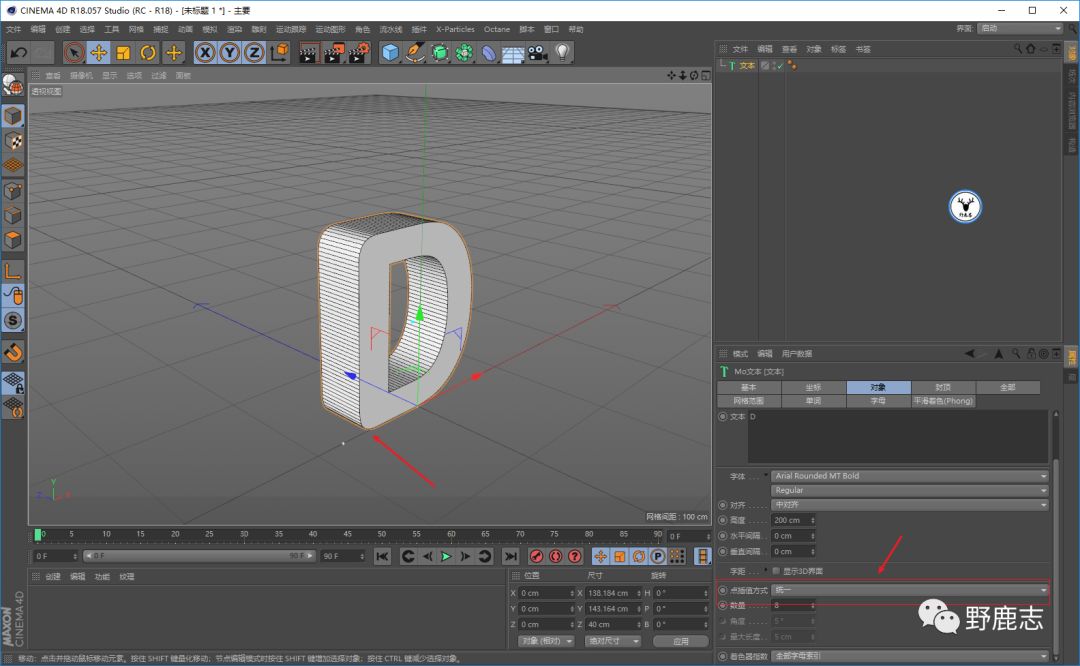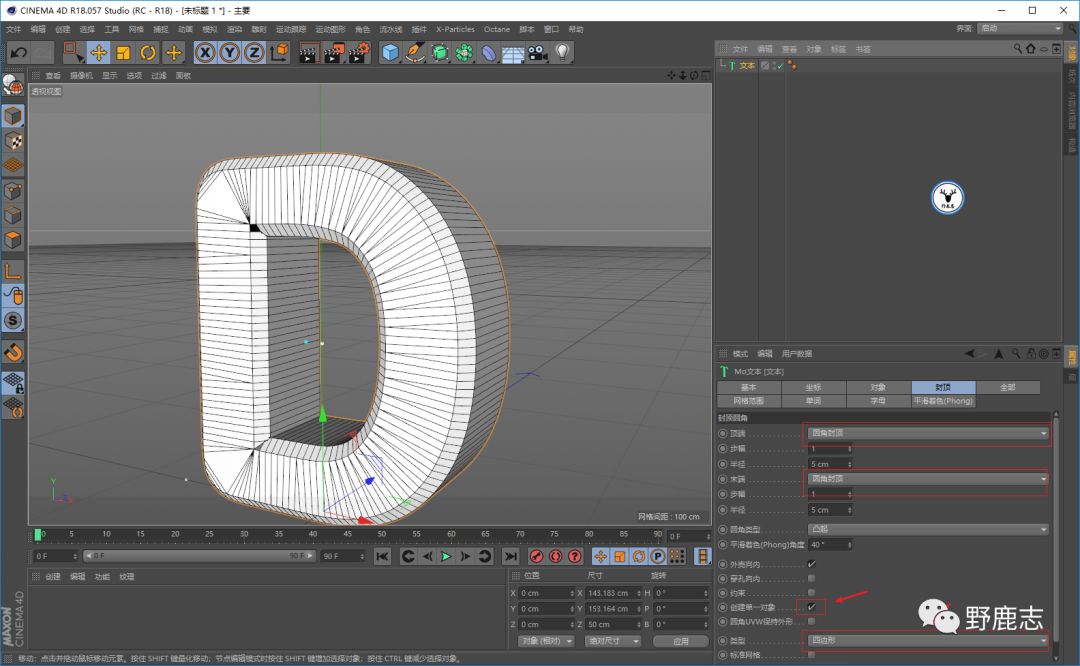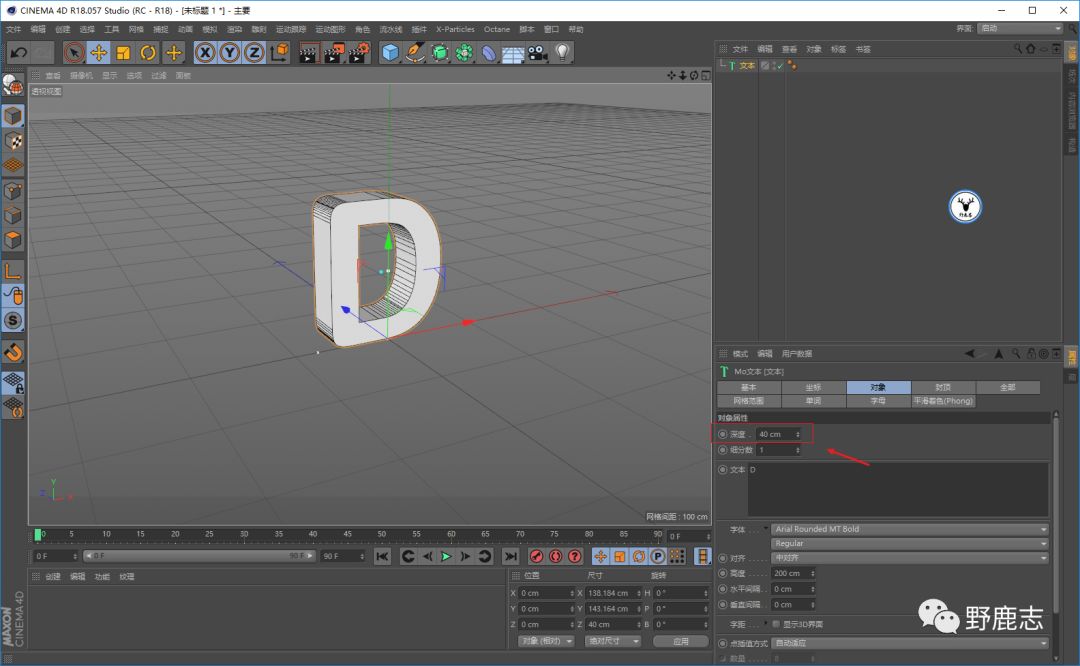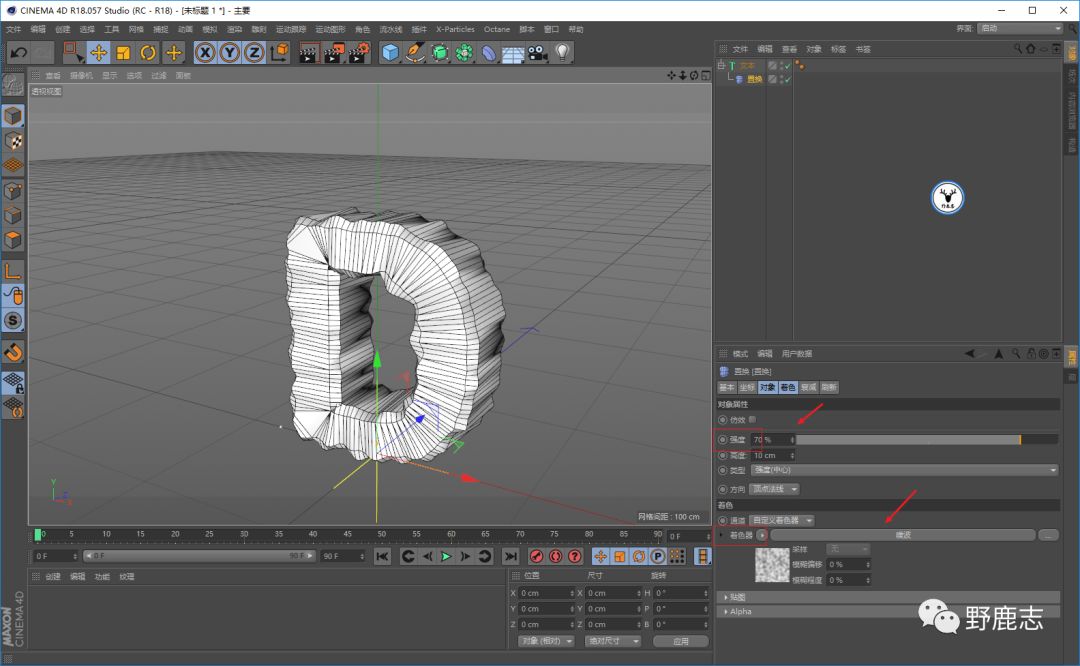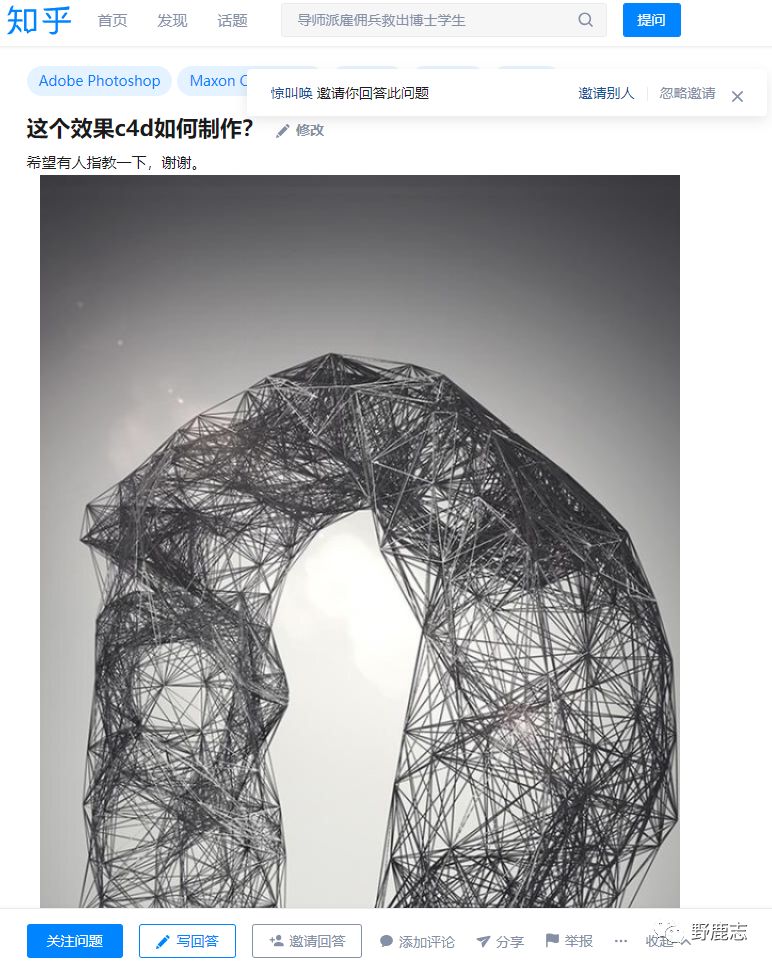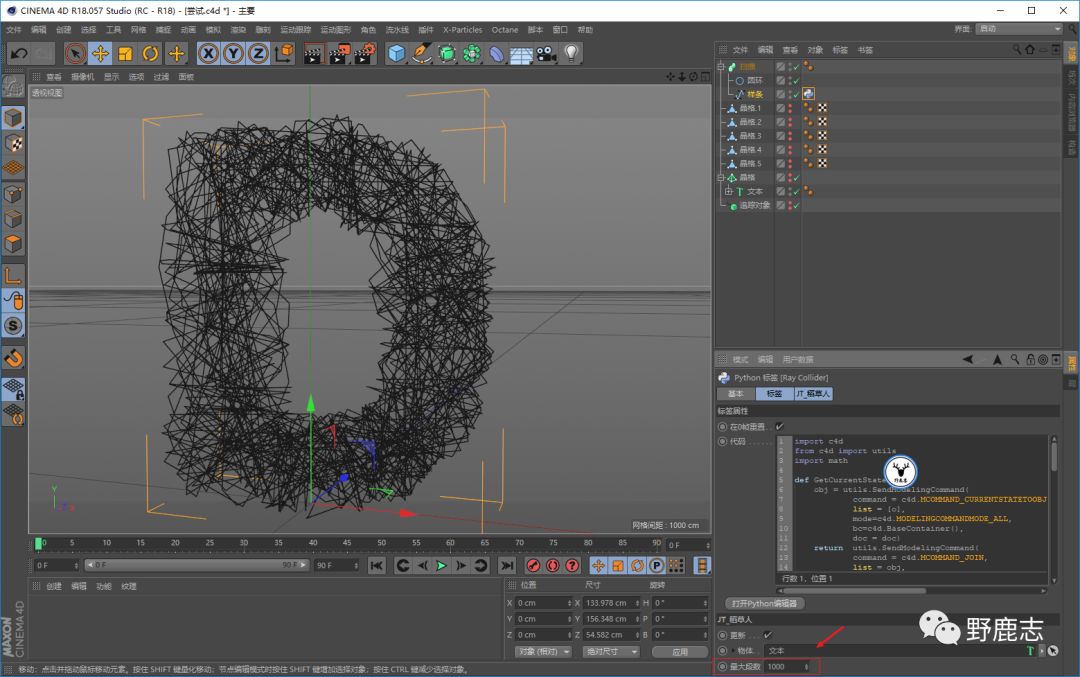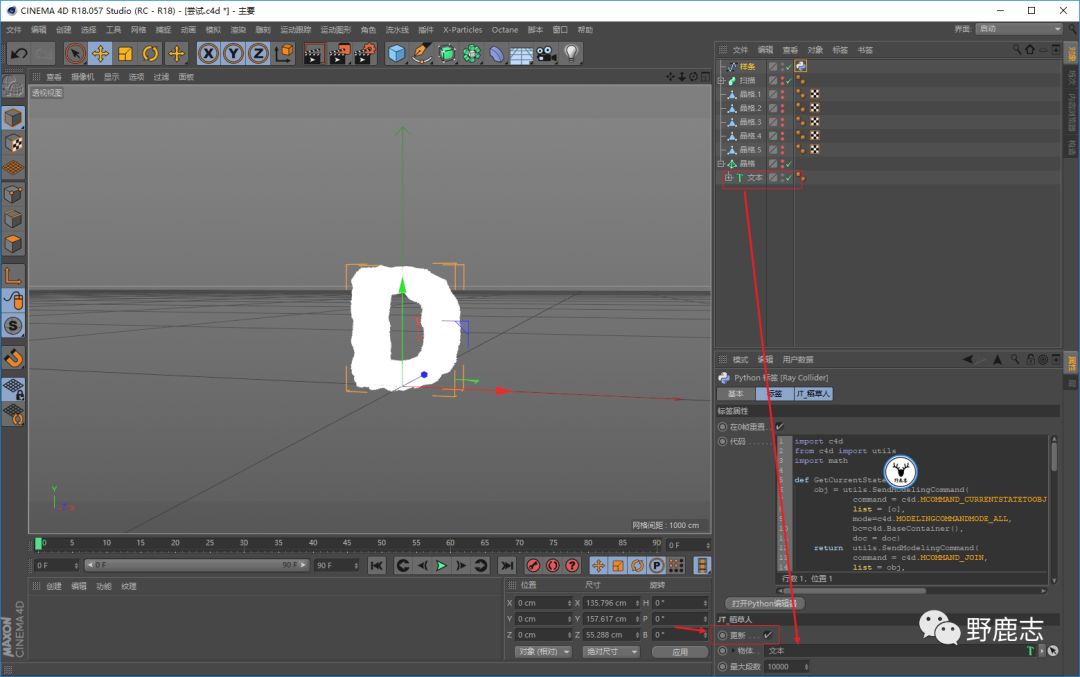
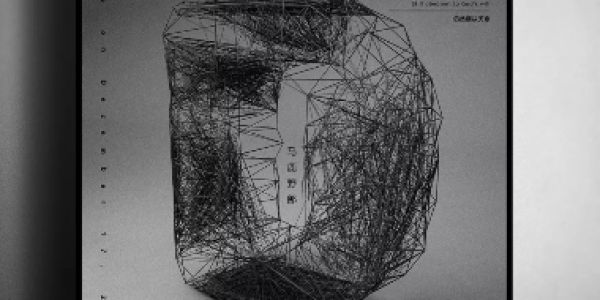
那种框架线条的效果是如何制作的?
我尝试了一下,大体方法其实不难,不过要做出好的效果还是需要花点功夫。
来吧,今天我们就用C4D来制作一个框架线条文字吧!
开始之前还是先大体分析一下原图,能够看出原模型字母的框架其实是有点low poly低多边形的感觉,所以我们要先做出一个低多边形的字母模型。
另外由于除了框架以外,框架内部还有许多不规则的线条,所以我觉得可能要做两层才可以。
第一层由于晶格是根据模型的布线来使模型产生变化,所以做好low poly的字母模型以后,我们尝试用晶格来做。
第二层的线条我打算用追踪对象来做,追踪对象不仅可以追踪路径,还可以把各个点连接起来。
大概初步分析就这么多,具体做的时候我们再看吧。
打开C4D,新建文本:
选择一个觉得合适的字体,适当的增加深度,由于我们后面要使用到晶格,所以把光影着色线条打开,方便观察:
点差值方式改为统一,让布线更加均匀一点:
封顶里面把圆角封顶选上,参数默认就可以了,勾选创建单一对象,类型选择为四边形:
添加一个置换变形器,着色面板添加一个噪波,然后适当的调整置换的强度,这一步不用多说吧:
再添加一个减面效果器,适当的调整强度,这样模型上的布线就都成了三角面:
如果你觉得线有点多,只要调整文本中点差值处的数量就可以了:
然后再添加晶格,修改圆柱和球体的半径,这样框架部分就做好了:
我们接下来再看看内部的那些线怎么做吧,选中所有对象,鼠标右键连接对象:
在选中连接后的晶格对象前提下,执行运动图形-追踪对象:
然后再把追踪模式修改为连接所有对象,这样对象就会基于模型的点添加出很多样条来:
但是原图的线是有些地方密集有些地方稀疏,并且字母的中间部分是没有连接起来的。
所以我们需要选中晶格对象,在点级别的模式先去手动框选一些点来进行删除:
重复上面连接晶格对象以后的步骤,把这些对象都放进追踪对象里,然后再删除多余的点,这里我就不重复啦:
弄完大概这个样子吧:
由于追踪对象做出来的线是样条,没有办法直接渲染的,所以新建圆环样条和扫描,让追踪对象和圆环成为扫描的子集。
当然你也可以添加毛发材质来渲染,这个看个人吧:
你还可以调整细节,例如圆环样条的半径大小以及追踪对象中的样条类型等,这个大家看着效果来吧:
基本上这样就差不多做好了。
当做完才发现好像有一款稻草人插件可以比较简单的来搞定这个效果。。。阿西BUG!
我们来看看这个插件如何使用吧,将之前的对象隐藏,然后如图所示新建空白样条:
直接把插件拖进C4D,然后双击红色箭头处,空白样条就会添加一个标签:
直接把文本拖到物体栏,然后把更新打上勾,对象就变成样条了:
同样这些样条是不能被渲染的,所以要用扫描或者毛发材质,这个就不用多说了吧:
不过我觉得今天的内容直接用插件没办法那么灵活的表现出原图中线条的部分稀疏部分紧密的效果。
而且还是得先用晶格做框架:
材质和渲染方面我就不多说了,总体来说无论是用C4D自带的物理渲染器还是用OC,都会比较卡,毕竟线很多。
所以建议可以先暂时关掉扫描,只留下晶格做出的框架部分,然后上材质打灯,搞完以后再开启扫描:
最后渲染出图以后,PS调调色,码字排版导样机看看效果吧: